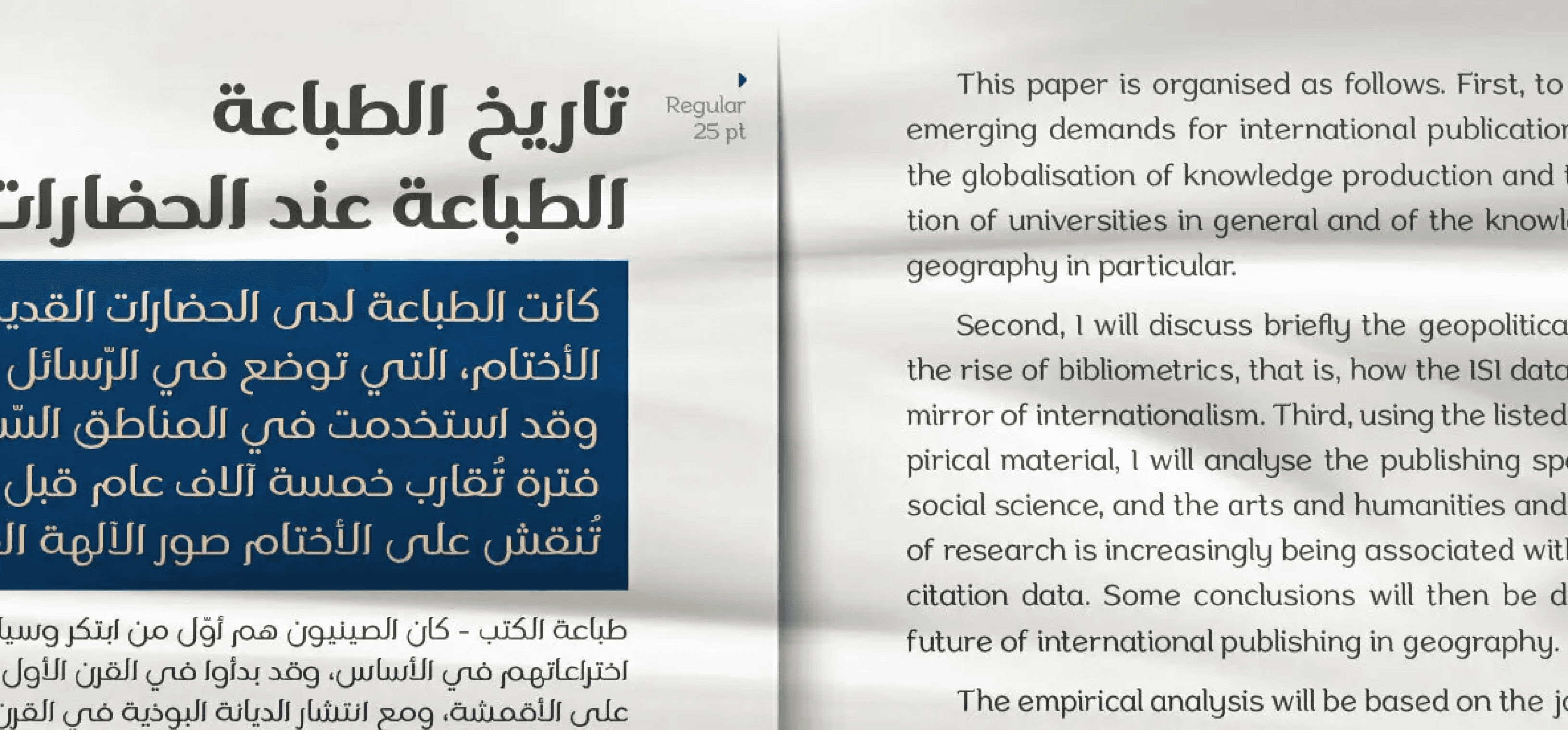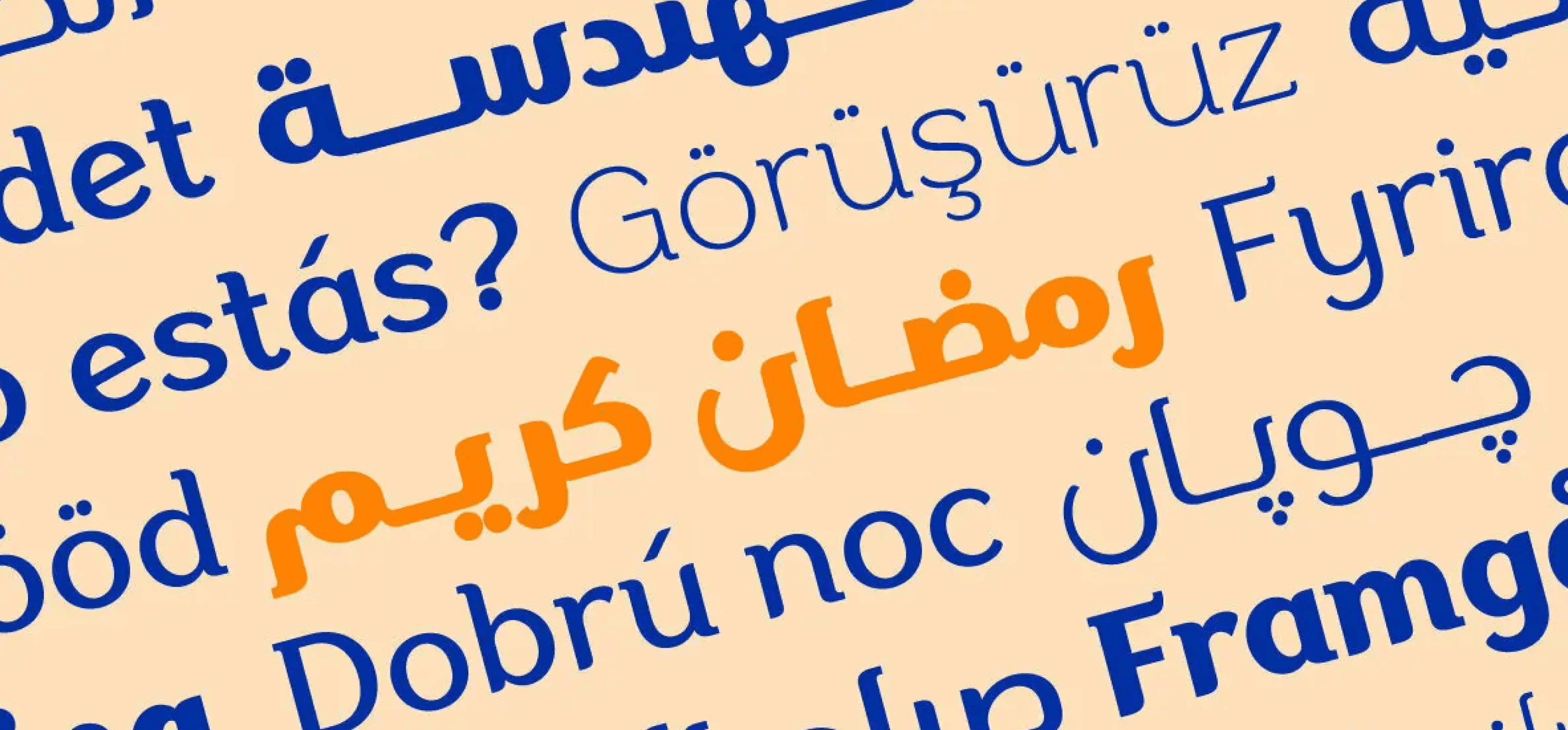
خط عربي لاتيني أنيق يجمع بين الحداثة والبساطة، يأتي بتصميم متوازن يدعم الكتابة باللغتين العربية واللاتينية بانسجام بصري مميز.
يتوفر بـ 9 أوزان متنوعة تشمل: Thin, ExtraLight, Light, Regular, Medium, SemiBold, Bold, ExtraBold, وBlack، مما يجعله مثاليًا لتصميم الشعارات، العناوين، والمطبوعات الإبداعية.